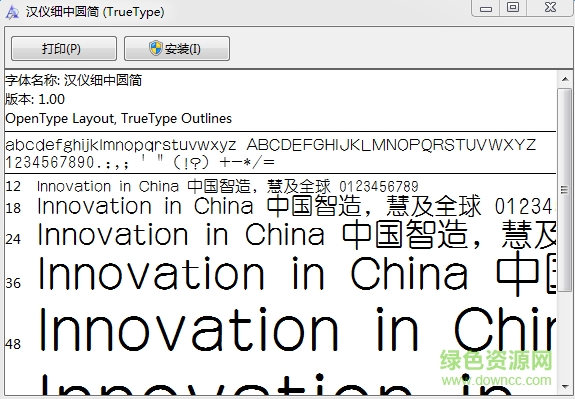
hye2gj字體是一款字形圓潤的電腦字體,寫出來的字粗細(xì)均勻,工整大氣,現(xiàn)在來綠色資源網(wǎng)下載,只需輕松的操作,就能讓你在自己的電腦上使用到這款有沒的字體!
hye2gj字體是漢儀細(xì)中圓簡,是一款非常端正的中文字體,字體端正,簡潔清晰,適合應(yīng)用于廣告設(shè)計、名片設(shè)計、包裝印刷、兒童產(chǎn)品設(shè)計等應(yīng)用。